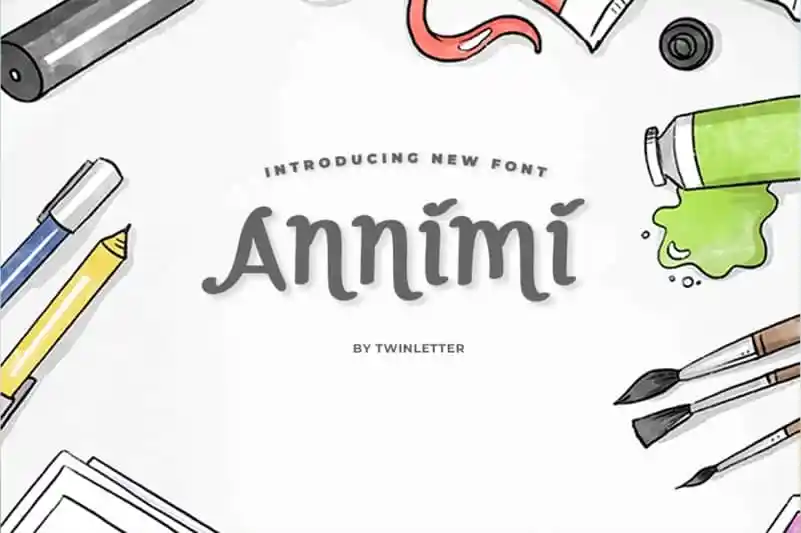
Annimi Script Font – Download Grátis
A Annimi Script Font é uma fonte escrita a mão que oferece um toque leve e divertido, cuidadosamente criado para ser amada por quem vê. Suas características descompromissadas criam um ar de simplicidade encantadora, tornando-a muito leitura confortável e versátil em qualquer contexto. Seja ela usada em fundos confiáveis ou como uma grande headline sozinha, a Annimi manterá sua personalidade única e original. Perfeito para designers que querem adicionar um toque de vida aos seus projetos, seja ele para sites pessoais, revistas ou editoriais digitais. Composto com cuidado por twinletter, este é o ideal fonte para aqueles que procuram uma escrita a mão que não perde sua elegância nem seu encanto na era digital.